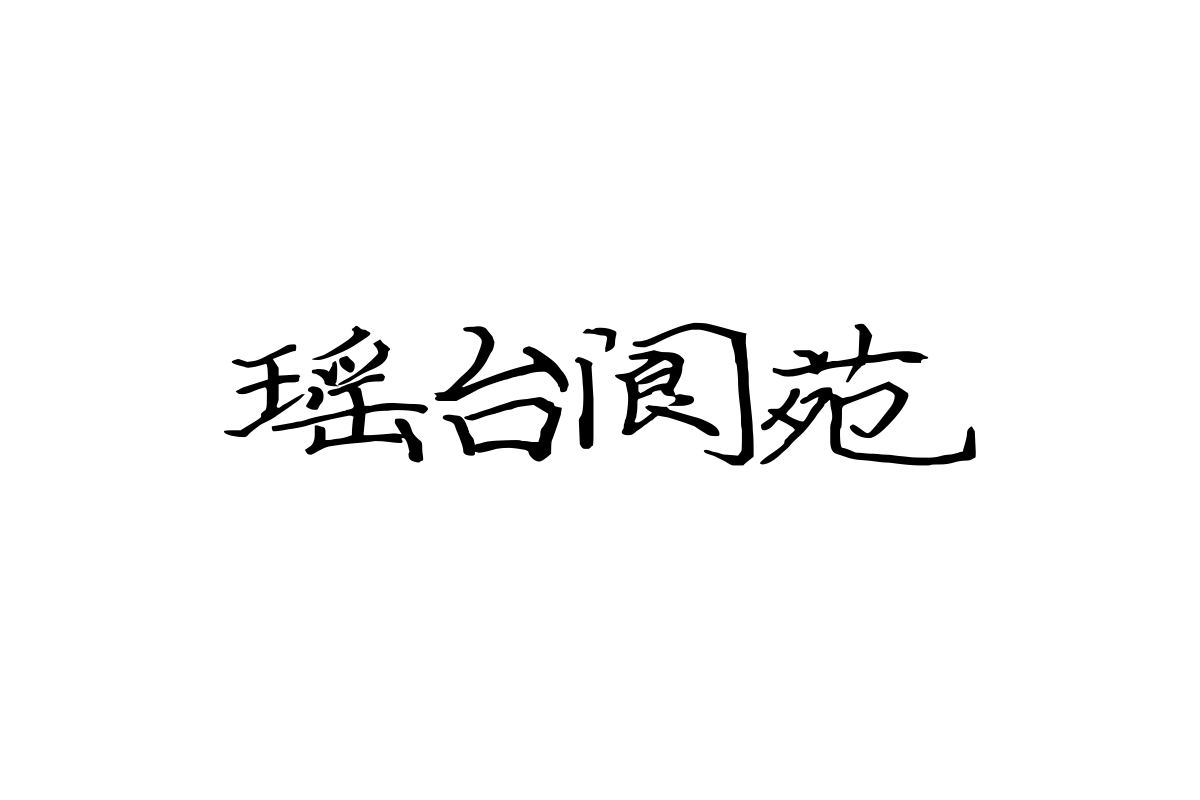
段宁硬笔隶楷字体是一种独特的书法风格,它融合了传统隶书的严谨与硬笔书法的流畅。这种字体的特点是笔画清晰、结构紧凑,既有隶书的古朴大气,又有硬笔书法的简洁明快。
段宁硬笔隶楷字体的特点如下:
1. 笔画清晰:段宁硬笔隶楷字体的笔画线条流畅,没有过多的装饰性细节,使得整个字体看起来更加简洁明了。
2. 结构紧凑:这种字体的结构紧凑,每个字的笔画都紧密相连,没有过多的空隙,使得整个字体看起来更加整齐有序。
3. 古朴大气:虽然是一种硬笔书法风格,但段宁硬笔隶楷字体仍然保留了隶书的古朴气息,给人一种庄重、大气的感觉。
4. 简洁明快:这种字体的风格非常符合现代人的审美需求,简洁而不失灵动,明快而不显生涩,使得整个字体看起来既美观又实用。
总的来说,段宁硬笔隶楷字体是一种非常适合现代生活的书法风格,它的出现为硬笔书法带来了新的活力和可能性。